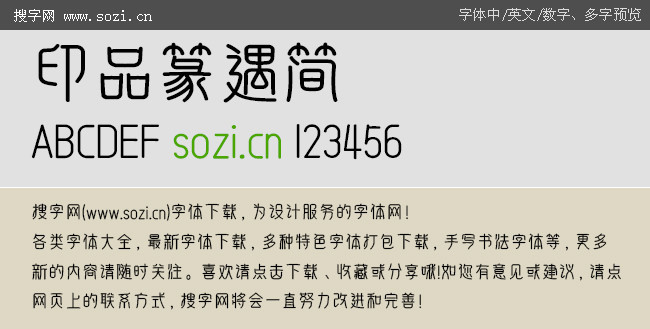
印品篆遇簡(jiǎn)
搜字網(wǎng)給大家提供一款印品篆遇簡(jiǎn)中文字體下載,該字體該字體纖細(xì)有規(guī)則,筆畫很有古代風(fēng)格,保存了古代書(shū)法的象形字特點(diǎn),筆鋒輾轉(zhuǎn)獨(dú)特有魅力。適用于海報(bào)設(shè)計(jì)、包裝設(shè)計(jì)、商業(yè)廣告等廣告設(shè)計(jì)。